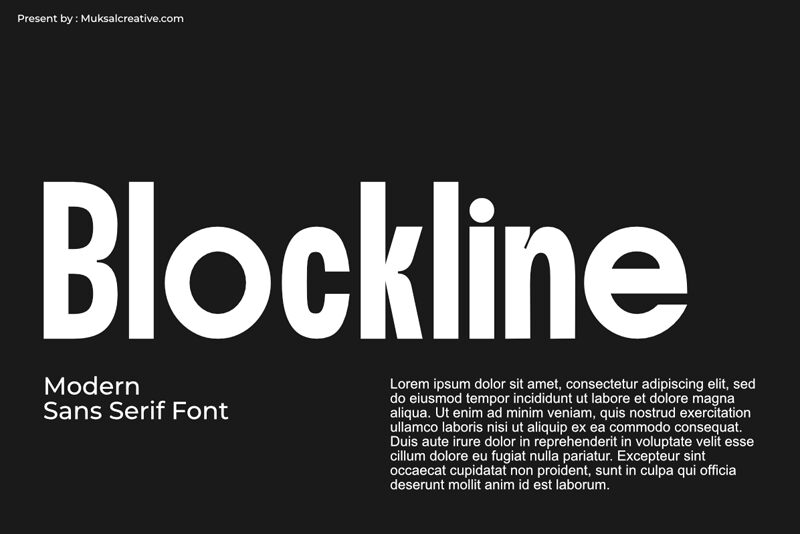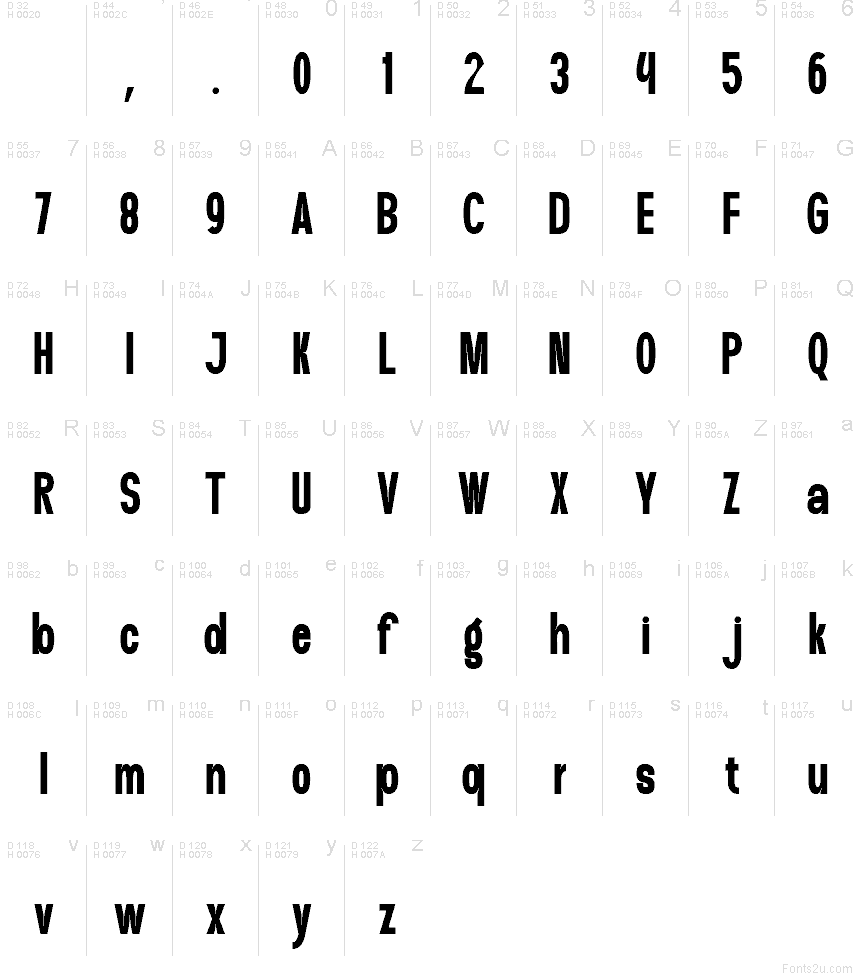
Blockline von Muksal Creative ist eine kostenlose serifenlose Schrift, die durch ihre hohe, kompakte Silhouette und ihre kräftige, massive Ausstrahlung besticht. Durch die wiederkehrenden geraden Seiten und abgerundeten Ecken wirkt das Schriftbild wie ein kompaktes Signage-Design, statt wie eine neutrale Alltagsschrift. Diese konzentrierte Form eignet sich hervorragend für Schlagzeilen, Album-Cover, Verpackungen, Event-Poster und Ladenbeschilderungen, wo es auf visuelle Präsenz ankommt. Sie verleiht auch Social-Media-Promos und Titelkarten eine solide, vertikale Note, wenn ein dichteres Layout gegenüber luftigen, geometrischen Abständen bevorzugt wird.
Blockline